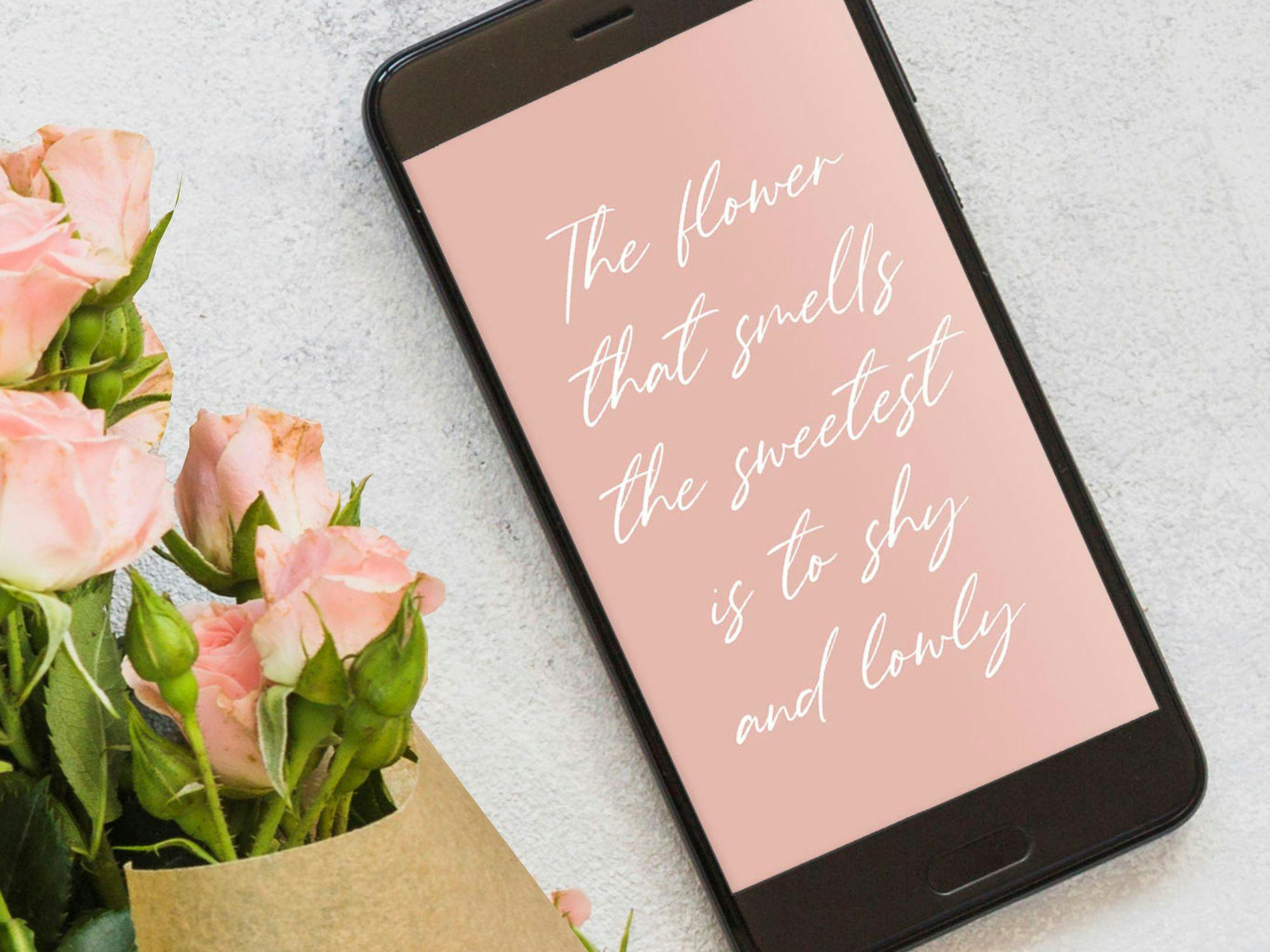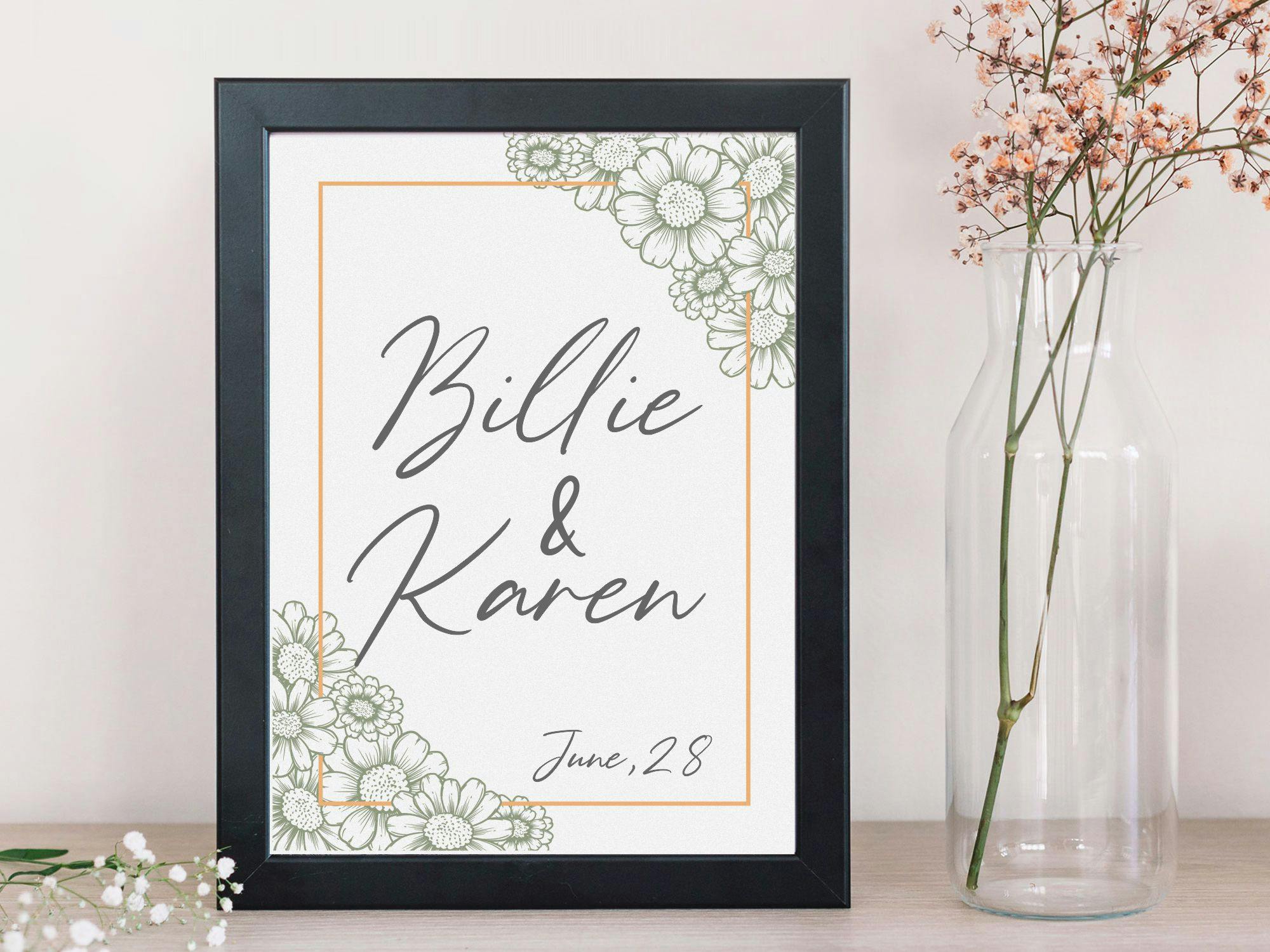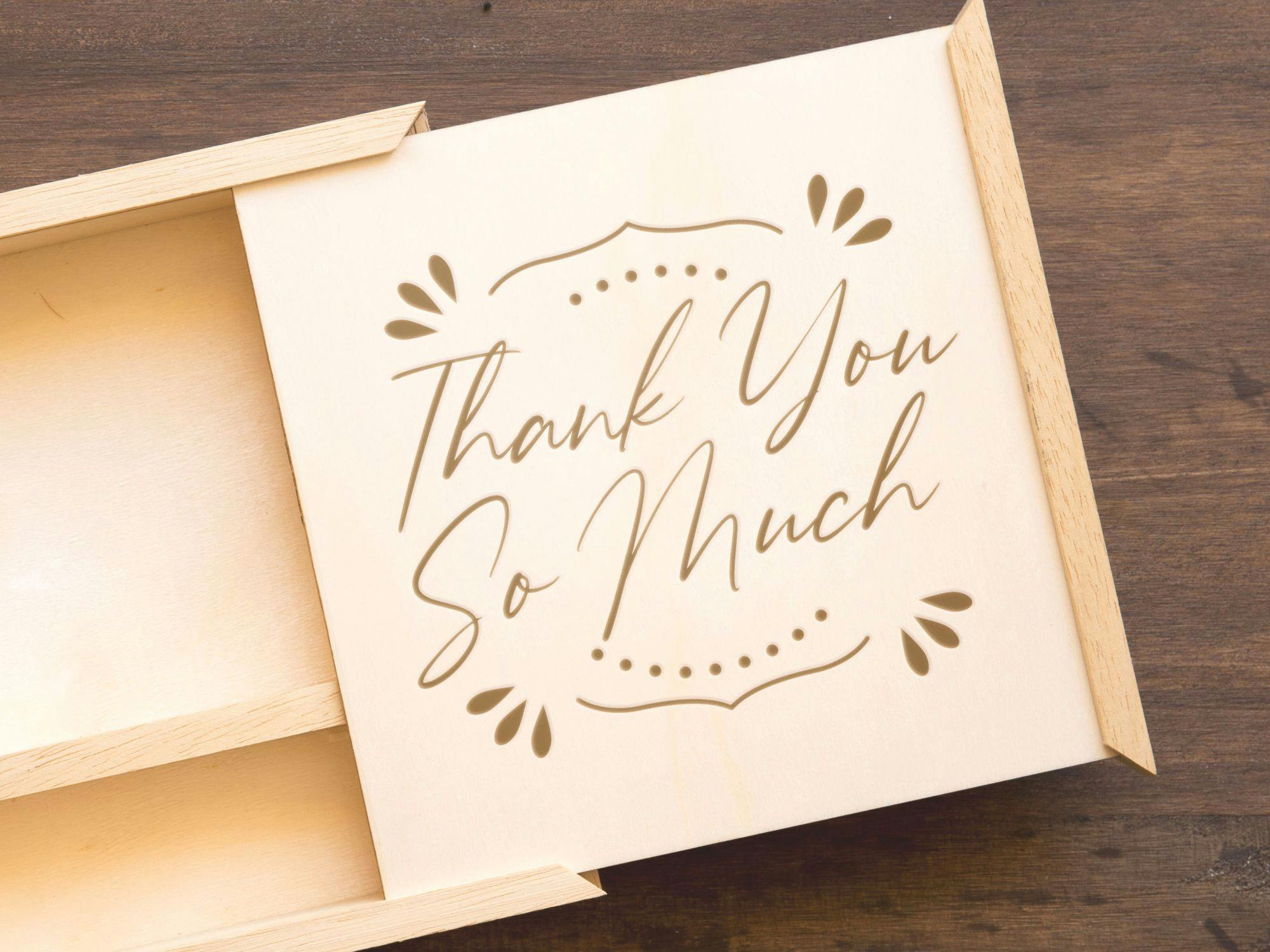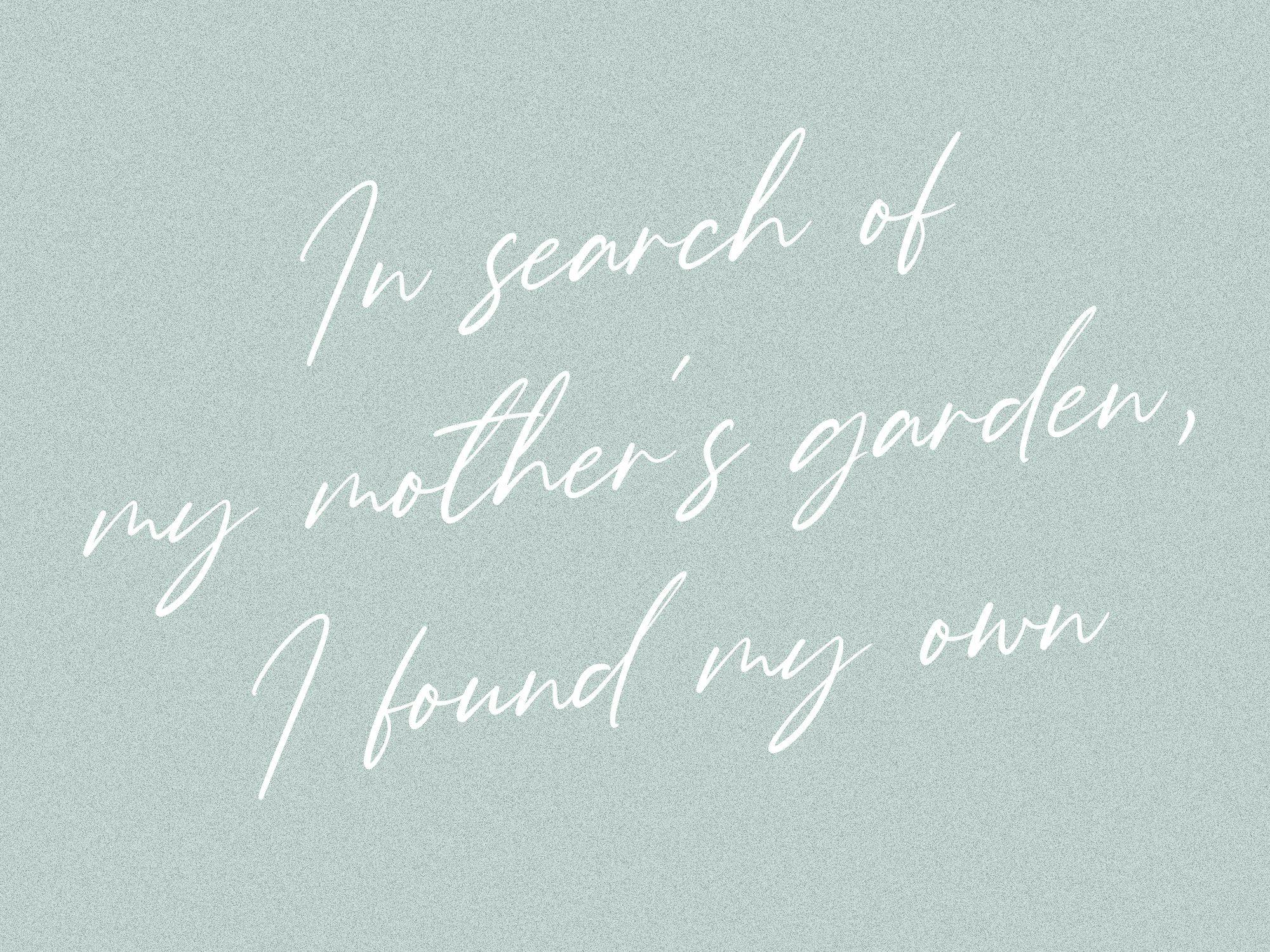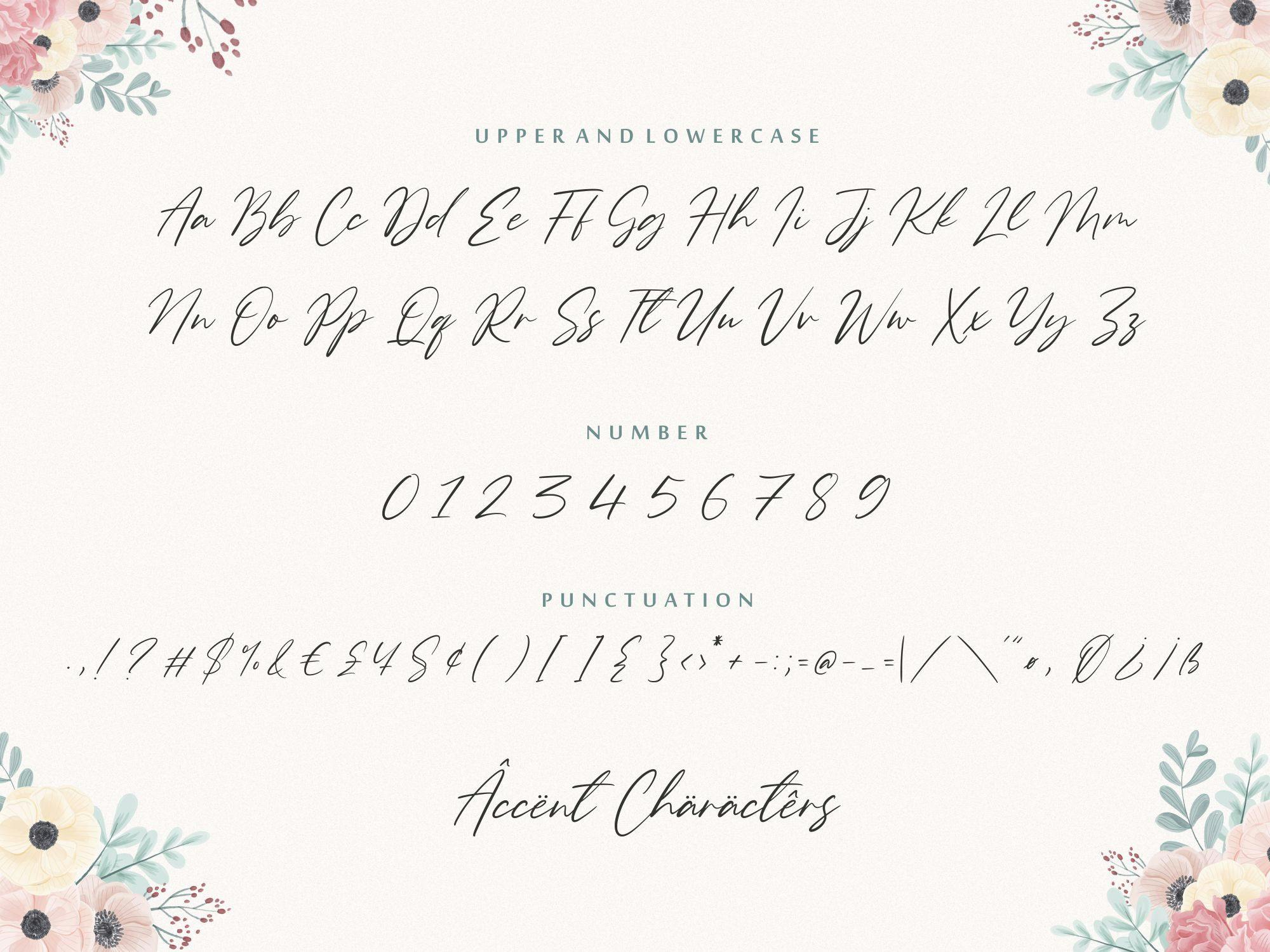
با افتخار، فونت Gardenisa را معرفی میکنیم.
Gardenisa یک فونت کالیگرافی مدرن و زیبا است.
این فونت برای بستهبندی محصولات، پروژههای برندینگ، مجلات، رسانههای اجتماعی، مراسم عروسی و یا حتی برای بیان کلمات بر روی پسزمینهها کاملاً مناسب است.